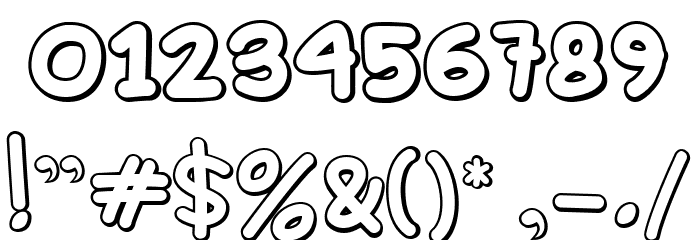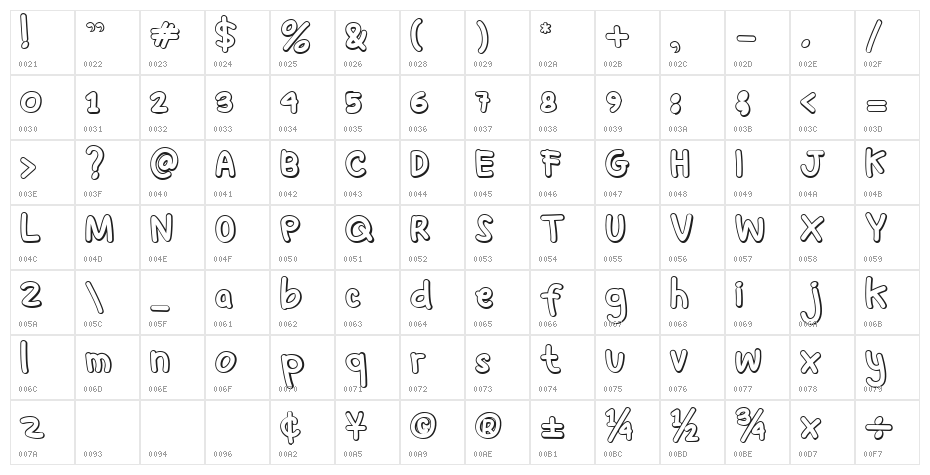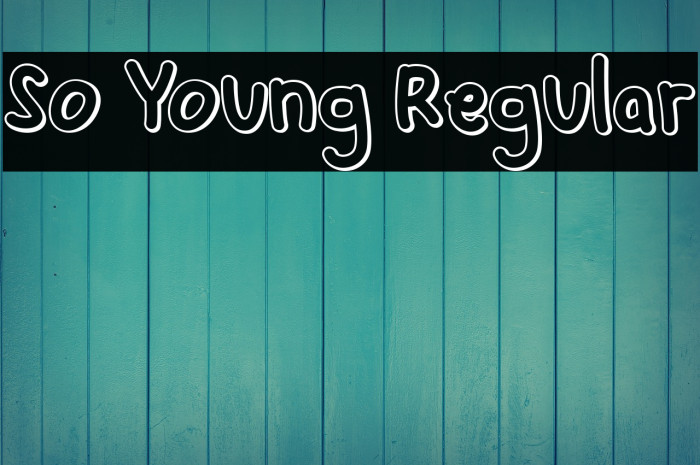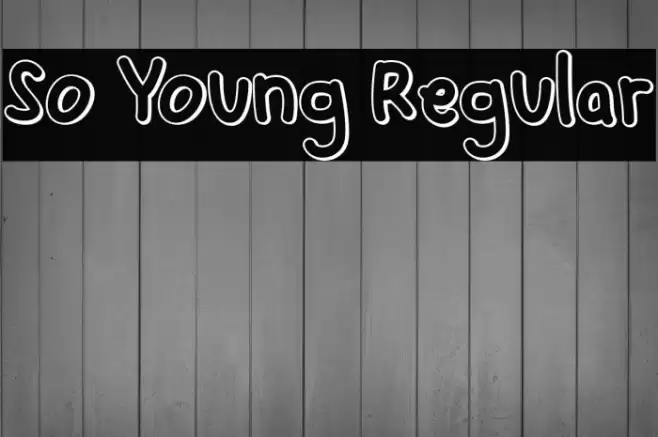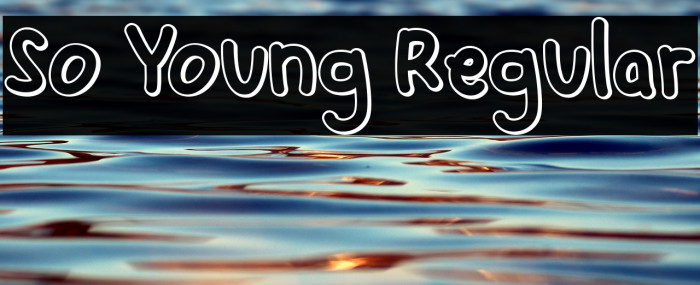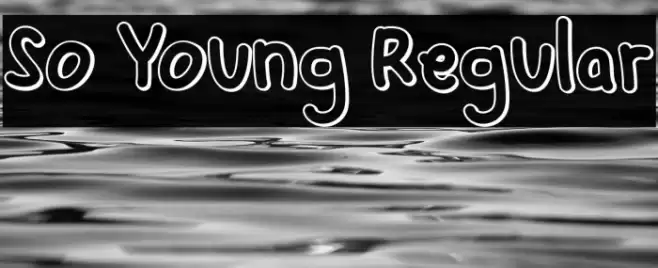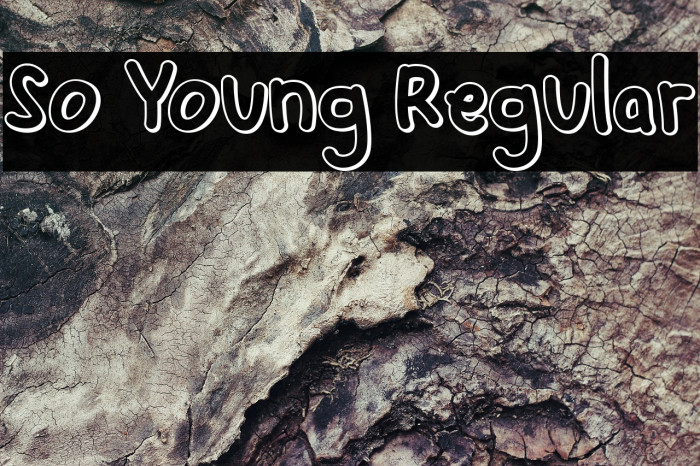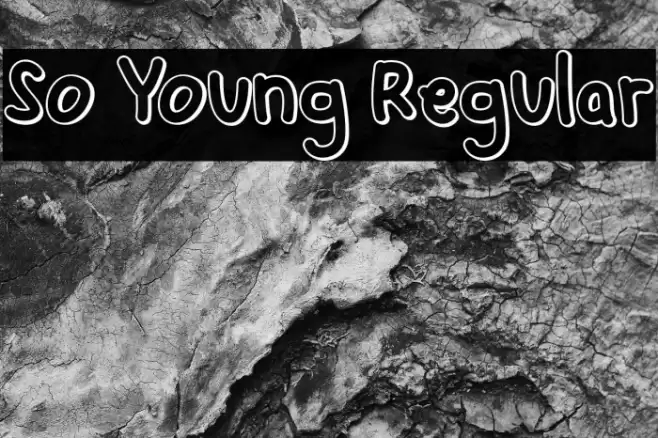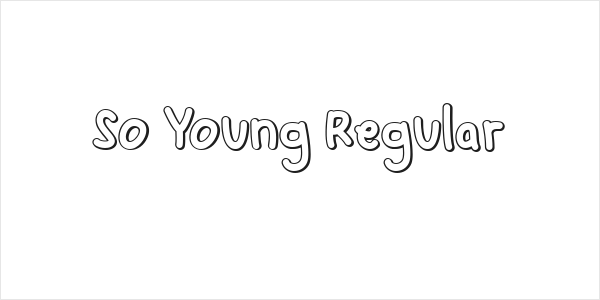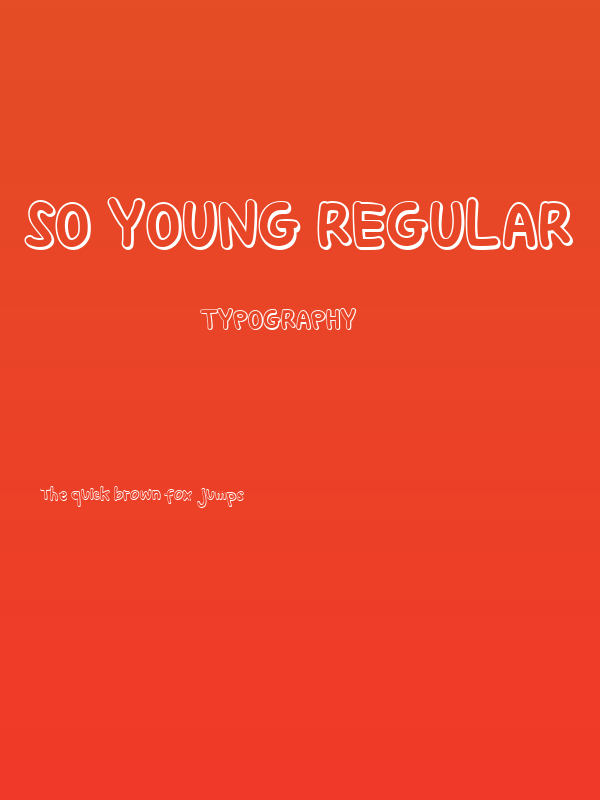
So Young Regular Font
| Estilo general | Playful, Whimsical |
| Proyectos propuestos | Ideal for children's books, comic strips, playful branding, and creative posters. |